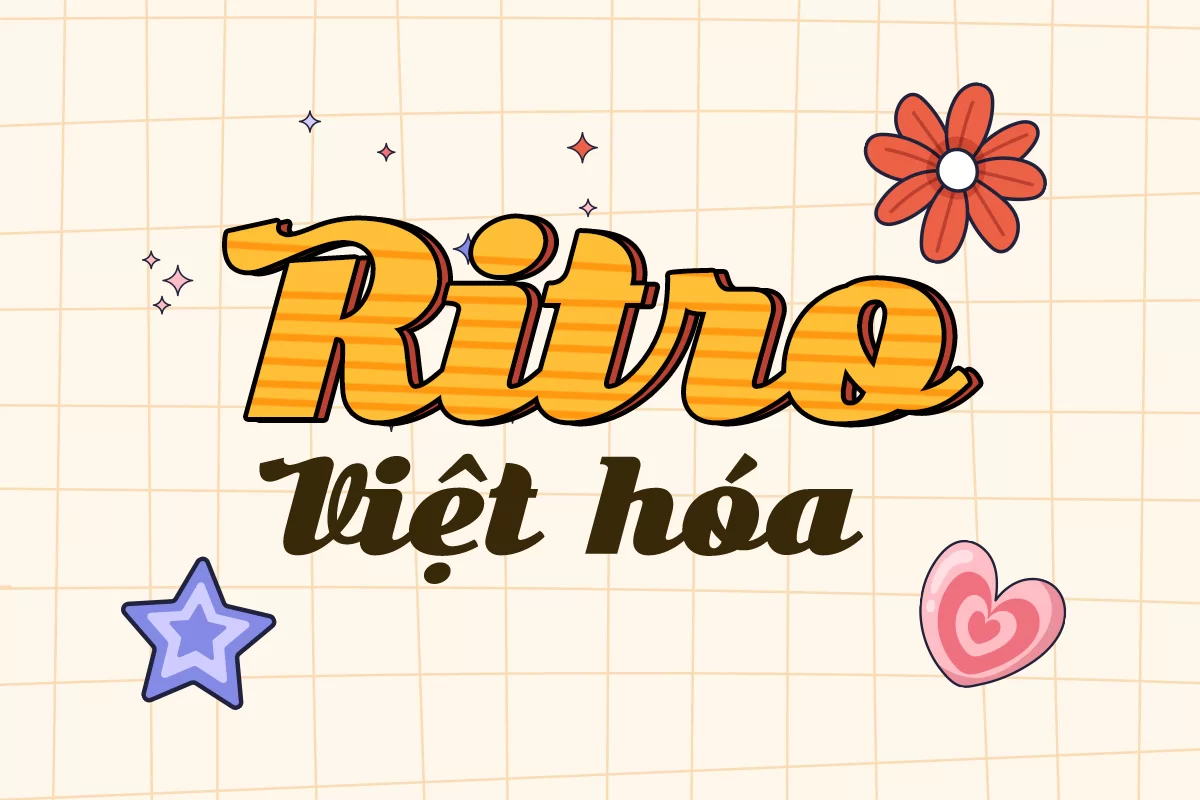
Ritro là một font chữ Việt hóa mang phong cách cổ điển, đậm chất retro của những thập niên xưa cũ. Với những đường nét mềm mại, dày dặn và các đường uốn lượn tinh tế, Ritro gợi nhớ đến các biển hiệu, bao bì và thiết kế quảng cáo cổ điển từ thế kỷ 20. Font bao gồm đầy đủ dấu tiếng Việt, phù hợp cho các thiết kế cần yếu tố hoài cổ như poster vintage, logo quán xá xưa, bìa sách cũ hay ấn phẩm mang màu sắc hoài niệm. Ngoài ra, Ritro còn cung cấp nhiều kiểu biến thể và glyph trang trí, giúp bạn linh hoạt sáng tạo trong từng thiết kế.